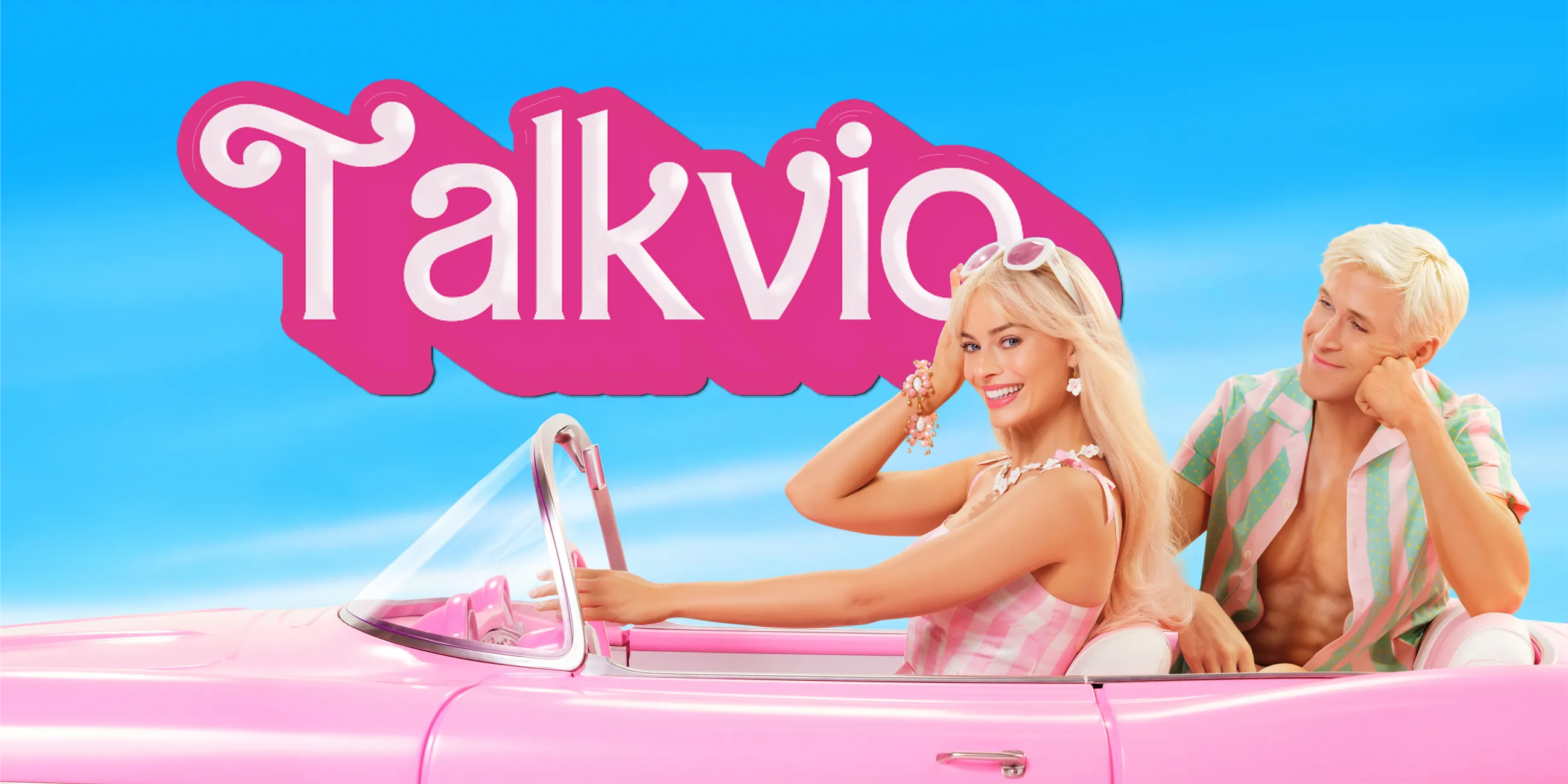
[моё] [КИНО-ШРИФТЫ: Барби]
Фильм «Барби» для своего названия взял довольно редко использующийся шрифт «Bartex». Но, по крайней мере тут обошлись без всяких модификаций.